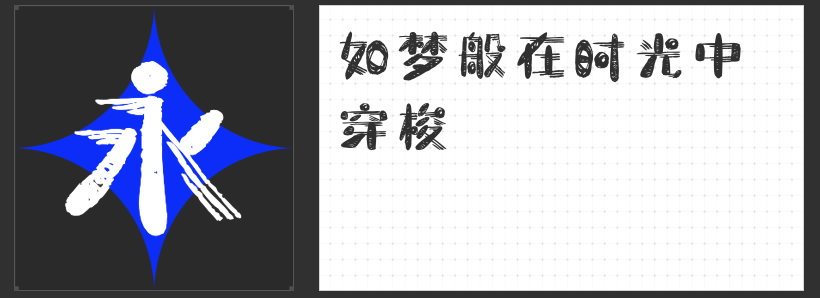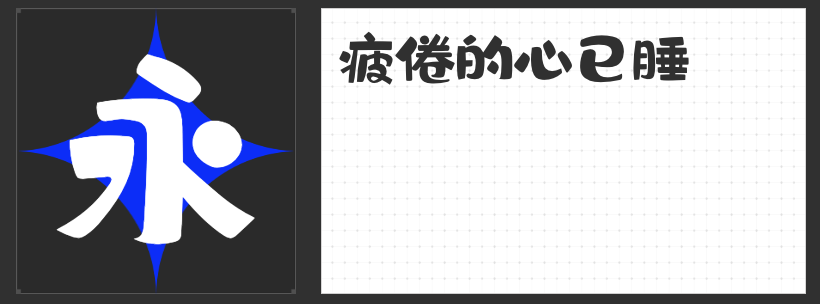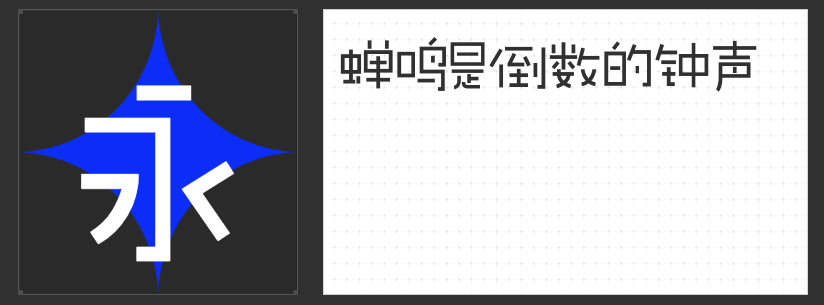
次元破壁:四款动漫风字体解锁视觉叙事新维度
当二维世界与三维现实碰撞,字体设计成为连接虚拟与现实的创意纽带。本文精选四款专为动漫场景打造的特色字体,以独特的视觉语言重构文字的叙事潜能,为漫画分镜、角色设定、动画标题等场景注入鲜活生命力。
一、字恋狂白日梦简
以“梦境解构”为核心理念,这款字体将凌乱线条转化为穿梭时空的视觉符号。笔画如被风吹散的信笺,在虚实交错间勾勒出潜意识流动的轨迹。设计师通过非对称结构与断裂笔触,营造出绘本中梦境与现实交织的朦胧感,特别适合奇幻类动漫的场景说明或内心独白呈现。
二、字恋狂澄空·拂风
基于手写质感开发的动态字体系统,通过“上松下紧”的黄金比例构建视觉重心。每个字符如同独立舞者,在统一节奏中展现个性姿态:部分偏旁部首的夸张变形与笔画断连处理,既保留了书写时的呼吸感,又通过字间距的韵律控制形成视觉动线。平直切角与流畅弧线的碰撞,恰似漫画中速度线与光影的完美融合。
三、励字敲可爱简
这款字体以“不完美的完美”为设计哲学,通过圆润手写线条与非常规笔画省略,构建出充满童真的视觉语言。略带倾斜的字形与适度留白,既保留了手绘的温度感,又通过几何化处理强化了现代动漫的视觉张力。特别适合少女漫标题或角色台词设计,能瞬间唤醒观众的情感共鸣。
四、励字憨憨简
采用“圆角矩形”作为基础形态模块,通过不同比例的弧形笔画重组,创造出具有Q版角色特质的字体系统。饱满的字腔结构与夸张的装饰性元素,使每个字符都如同会说话的动漫配角。这种将几何理性与萌系感性完美融合的设计,尤其适用于儿童动画标题或表情包设计。
这四款字体通过形态解构、节奏控制与情感投射,重新定义了文字在动漫场景中的存在方式。当字体成为叙事的一部分,每个笔画都在讲述属于自己的故事,为二次元世界打开更多想象可能。